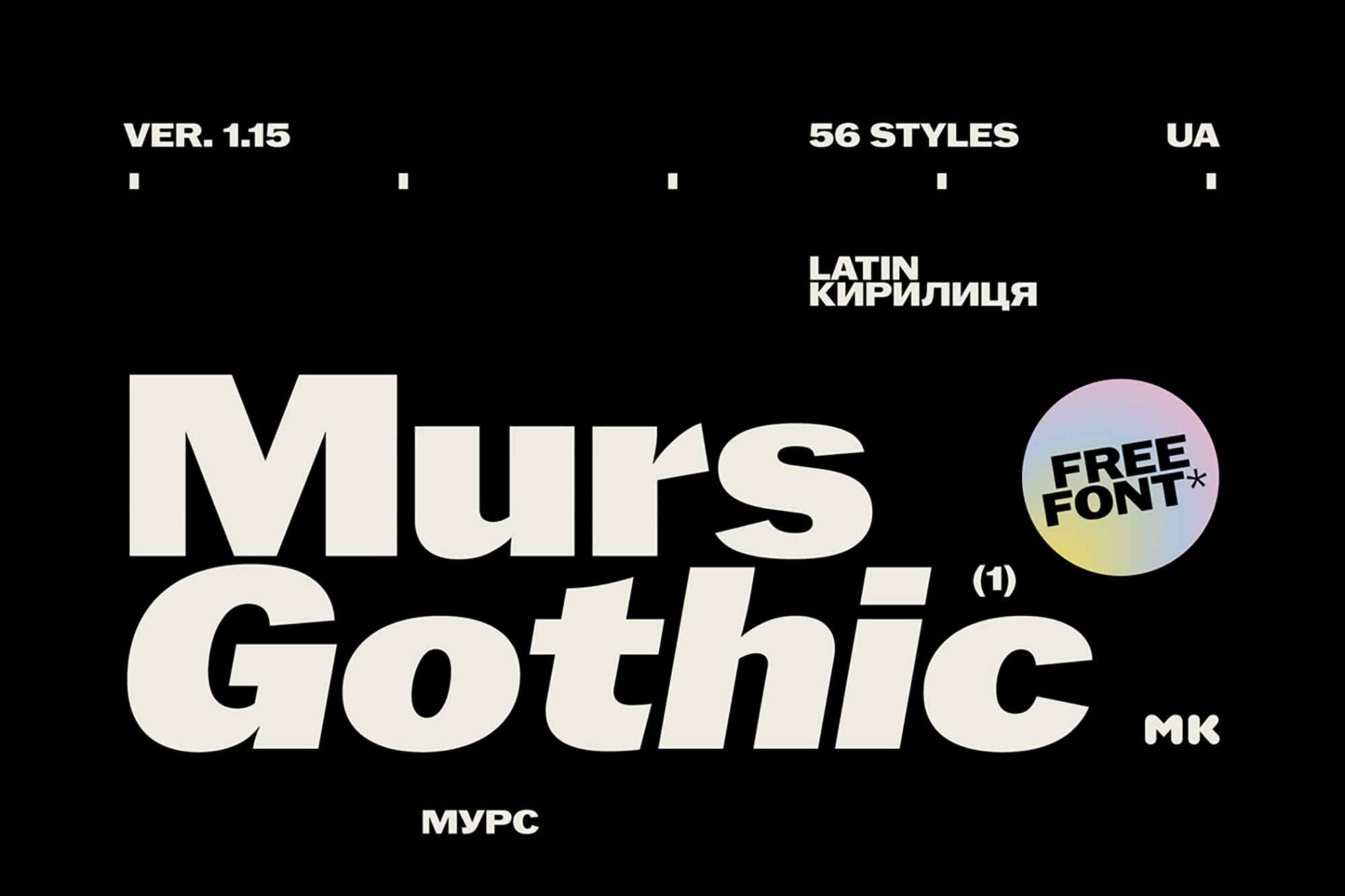
Murs Gothic Font – Download Grátis
A Murs Gothic é uma fonte sans-serif bold que traz ligaturas, símbolos, alternativas e mais de 694 caracteres. Esta tipografia é extremamente flexível, oferecendo 56 estilos, tornando-a uma excelente adição para os recursos do seu banco de dados de design. A Murs Gothic se adapta perfeitamente a designs impressos e digitais, como cartazes, revistas, websites e aplicativos móveis. Esse recurso gráfico é perfeito para designers que estão buscando adicionar mais opções ao seu catálogo de fontes para aprimorar os seus projetos.